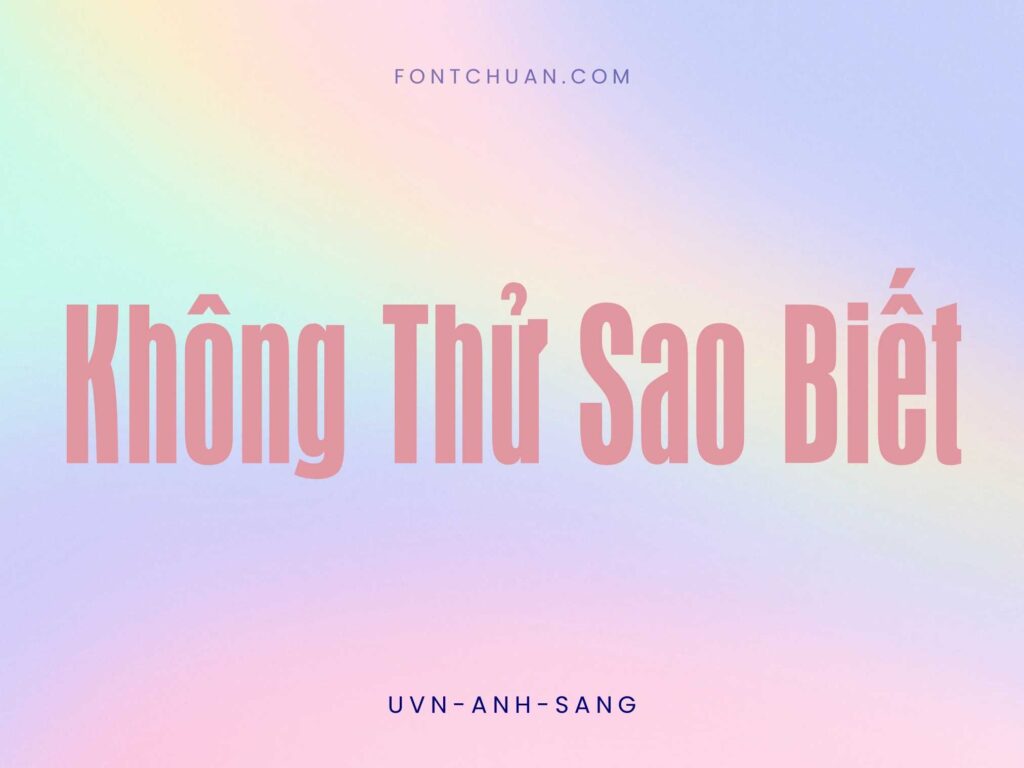
Font UVN Anh Sang Việt Hóa
UVN Anh Sáng là một phông chữ sans-serif hiện đại, được thiết kế bởi Tom Trương vào năm 2001. Phông chữ này có kiểu dáng đơn giản, rõ ràng và dễ đọc, phù hợp cho nhiều mục đích sử dụng khác nhau. Với thiết kế gọn gàng và tinh tế, UVN Anh Sáng giúp tăng cường tính thẩm mỹ và chuyên nghiệp cho các dự án thiết kế. Phông chữ này đã được Việt hóa, hỗ trợ đầy đủ các ký tự tiếng Việt, giúp người dùng tại Việt Nam dễ dàng sử dụng trong các dự án sáng tạo của mình.
Với thiết kế đơn giản và hiện đại, UVN Anh Sáng phù hợp cho các ứng dụng như thiết kế đồ họa, quảng cáo, biên tập văn bản và các ấn phẩm truyền thông. Trong lĩnh vực sự kiện, phông chữ này có thể được sử dụng trong các dịp như lễ hội, hội nghị và các sự kiện văn hóa. Ngoài ra, UVN Anh Sáng cũng thích hợp cho các ngành nghề như giáo dục, công nghệ và truyền thông.